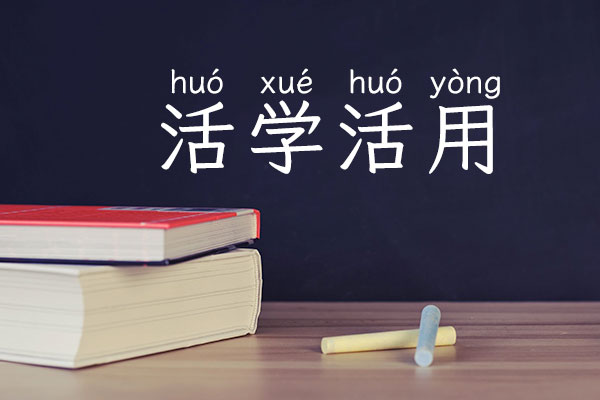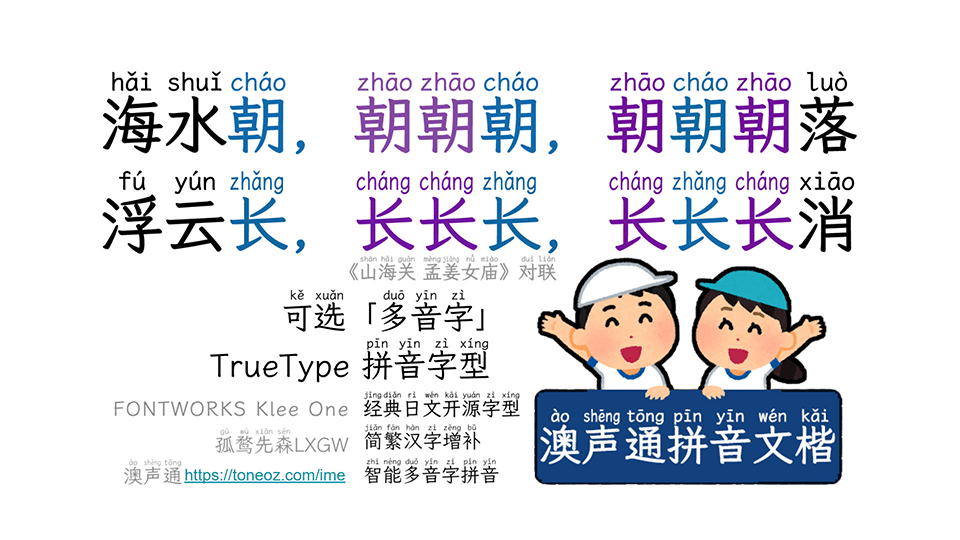
澳声通拼音文楷
澳声通拼音文楷这款的字体是由克利 Klee One 和霞鹜文楷两款成熟的开源字体为基础制作而成,无论简体还是繁体基本上不存在缺字。
澳声通拼音文楷的优势
1. 字体质量:基于两款顶级开源字体的澳声通拼音文楷,不仅避免了缺字的困扰,而且对多音字的支持也达到了前所未有的高度。无论是在阅读还是在设计应用中,都能为用户带来流畅的阅读体验。
2. 字重选择:令人欣喜的是,澳声通拼音文楷提供了3个字重供用户选择。这使得设计师可以根据自己的需求,更加灵活地调整字体粗细,从而创造出独特的视觉效果。
澳声通拼音文楷效果预览
澳声通拼音文楷字体效果预览